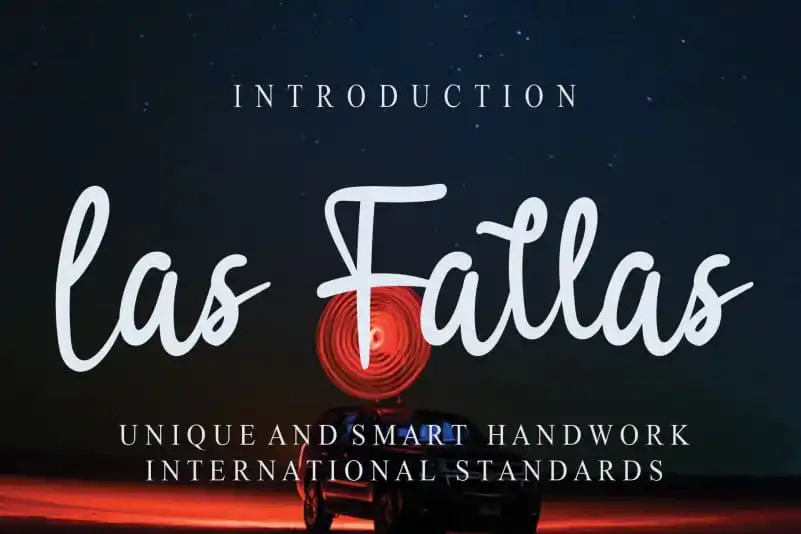
Las Fallas Script Font – Download Grátis
Aqui está uma descrição em português do Brasil para a página de download da fonte ‘Las Fallas Script Font’, mantendo as regras e características solicitadas: Composto por linhas fluidas e riscos delicados, Las Fallas Script é uma fonte escrita à mão perfeita para personalizar qualquer design com um toque poético. Essa elegante fonte não só adicionará autenticidade a seus trabalhos gráficos, mas também as dará um toque único e memorável. Com o seu designer criativo, esta fonte oferece uma experiência de escrita à mão sem igual, capaz de criar letras vívidas e fluidas que podem ser adaptadas para qualquer tipo de projeto, seja em logotipos, editoriais gráficos ou arte digital. Com suas linhas suaves e sua disposição única, Las Fallas Script é perfeita para projetos que exigem um toque de charme e originalidade. Se você está buscando uma fonte escrita à mão especializada em criar um impacto visual profundo em qualquer projeto que esteja trabalhando no momento, Las Fallas Script é a escolha certa. Seu design fluido e arrojado tornará suas criações gráficas mais memoráveis. Sinta-se livre para experimentar o aspecto único dessa fonte. É perfeitamente adequada para criar um projeto com um toque pessoal, onde você pode expressar seu estilo de uma maneira única e inovadora.